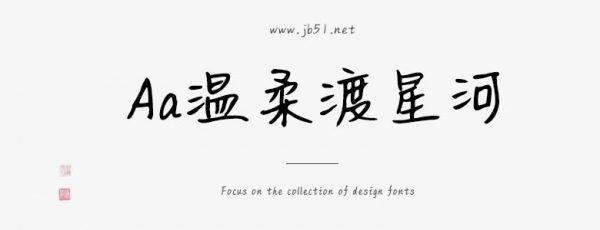
Aa溫柔渡星河是一款不錯(cuò)的藝術(shù)字體,由Aa字庫出品,字體筆觸適中,書寫流暢,擁有字符數(shù)10133和字形數(shù)10113,具有很好的視覺感,適合應(yīng)用于藝術(shù)設(shè)計(jì)、平面宣傳設(shè)計(jì)、網(wǎng)頁設(shè)計(jì),書法字帖等領(lǐng)域,需要的朋友可以前來本站下載。